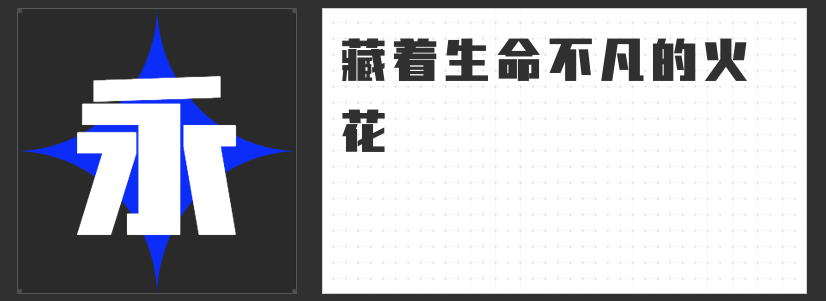
四款设计力作:解锁视觉表达的多元美学语言
在当代设计语境中,字体不仅是信息载体,更是塑造品牌气质、传递情感张力的核心媒介。本文精选四款风格迥异的字体,它们以独特的结构语言与视觉韵律,为设计师提供突破常规的创意工具。
一、高手庆科帅黑体 大黑
这款以几何线条构建的倾斜黑体,通过6度微倾设计打破静态框架,在硬朗骨相中注入速度感。中宫舒展的布局确保多字符排列时的呼吸感,横竖笔画的粗细对比强化视觉锚点,而折角处的钝化处理则消解了直线的冷硬感。其西文字符同步采用直线切割与倾斜设计,形成中英文浑然一体的视觉体系,尤其适合需要展现科技感与现代性的设计场景。
二、造字侠灵霄简繁 传神
从《西游记》的仙侠意象中汲取灵感,这款硬笔手写字体以刚劲笔锋重构古典气韵。笔画起收处的利落切角与均匀布白,既保留了碑刻书法的金石质感,又通过适度夸张的捺画与勾挑赋予动态势能。繁简体同步开发的设计考量,使其在文化类海报、影视标题等场景中,既能承载传统文化的厚重感,又不失现代审美语境下的传播效率。
三、励字志向黑简 大粗
圆体与黑体的基因重组,在这款字体中催生出独特的视觉性格。外圆角的弧度处理巧妙中和了黑体的机械感,而饱满的字腔结构则确保小字号下的清晰可读性。针对数字屏幕的优化设计,使其在高清显示与低分辨率场景中均能保持字形稳定性,成为移动端界面、信息图表等领域的理想选择。
四、高手平方北半川劲黑体
以反常规的竖粗横细结构颠覆传统黑体范式,这款字体通过方硬轮廓与笔画粗细的戏剧性对比,构建出充满张力的视觉符号。去圆角化的处理强化了字形的图形化特质,使其在品牌LOGO、包装设计等领域,既能独立成为视觉焦点,也可通过组合排列形成富有节奏感的模块化系统。
这四款字体以差异化设计语言,为不同维度的创意需求提供解决方案。它们或以理性结构诠释现代美学,或以文化基因激活传统意象,共同拓展着字体设计的可能性边界。